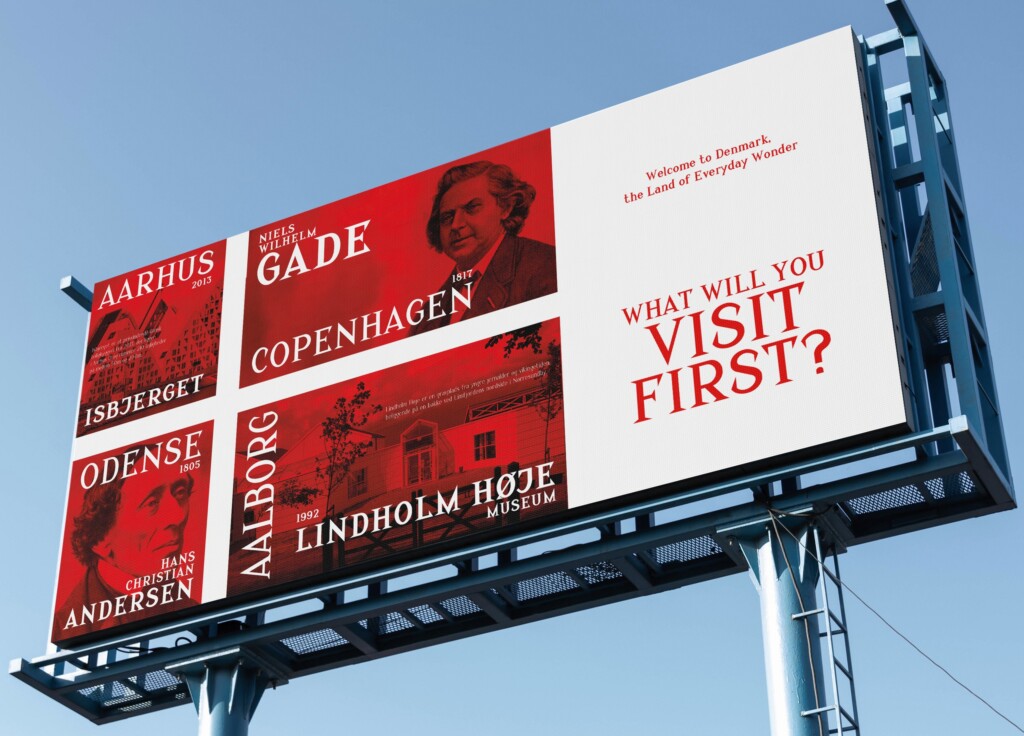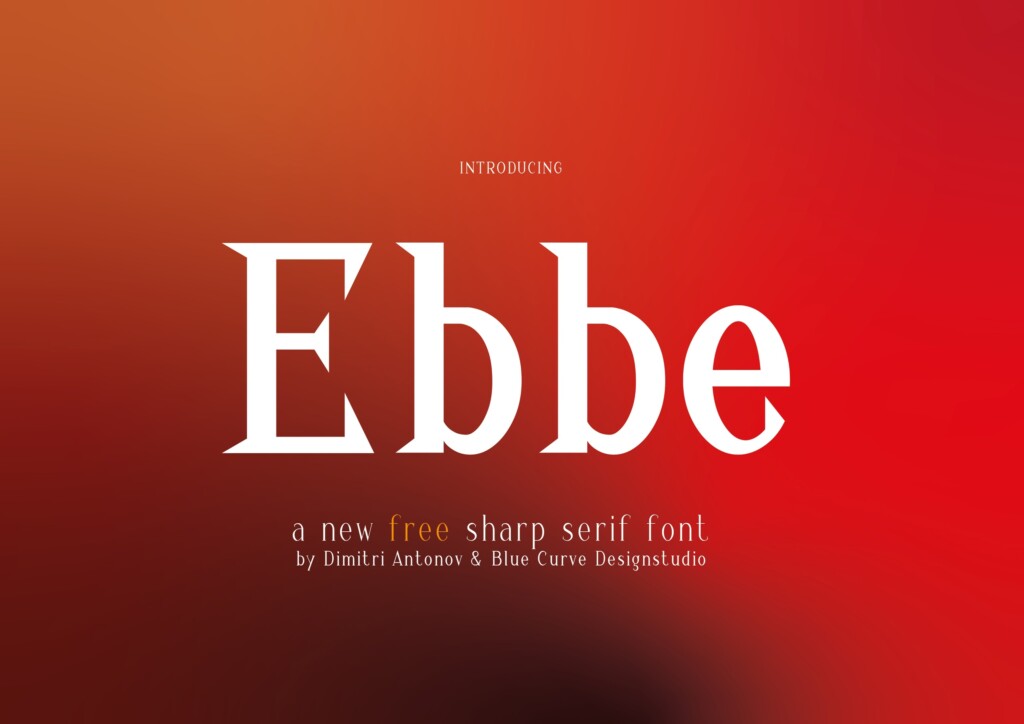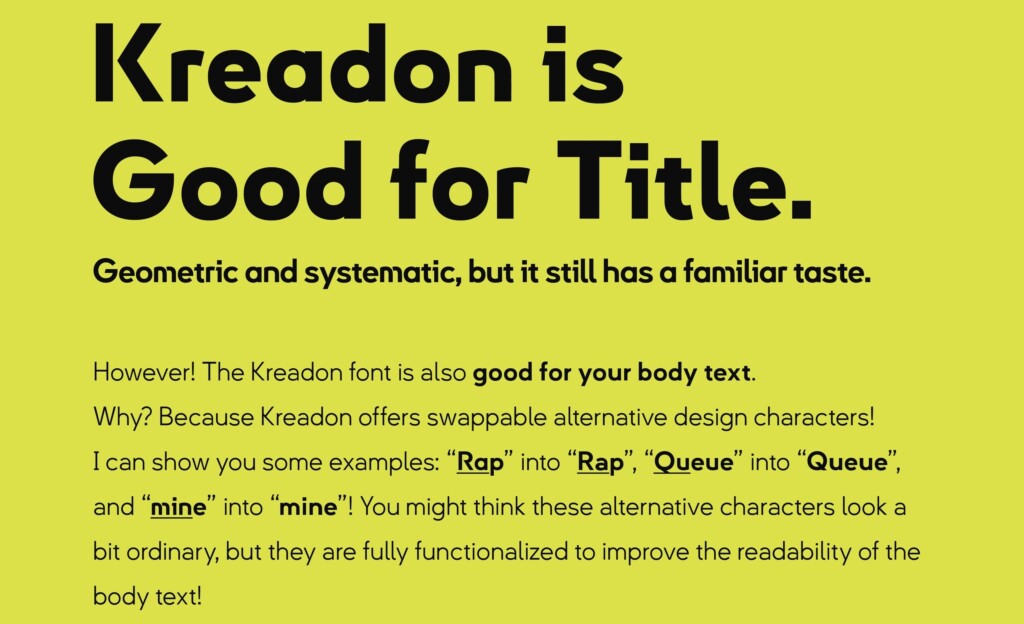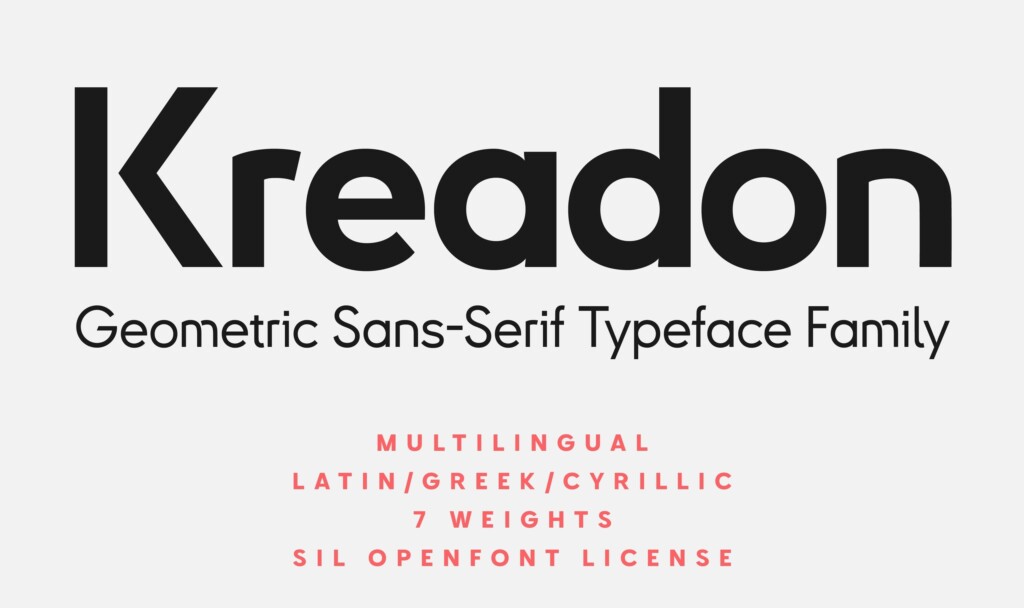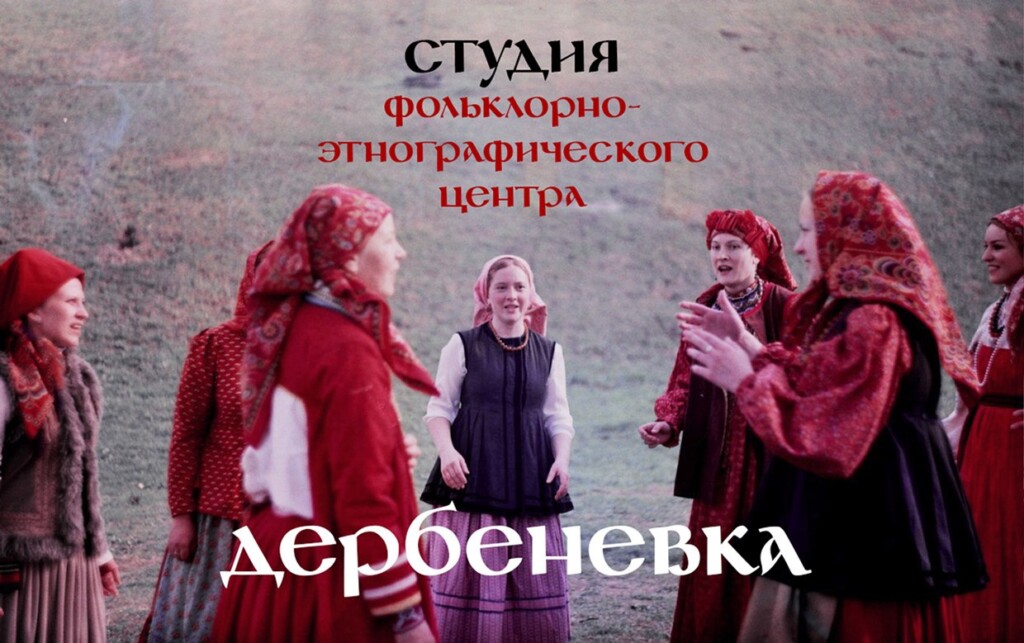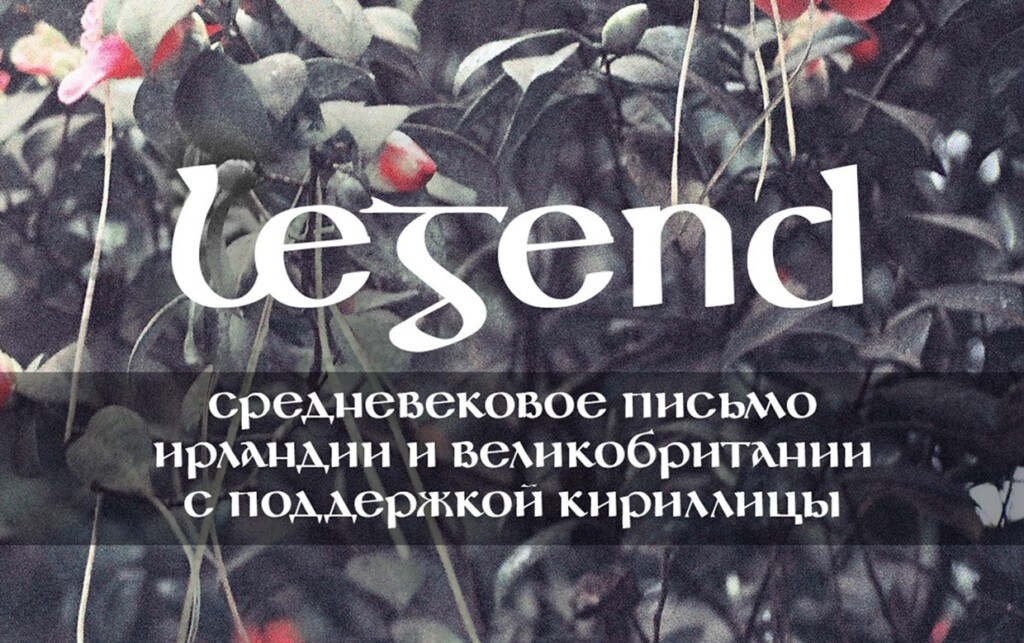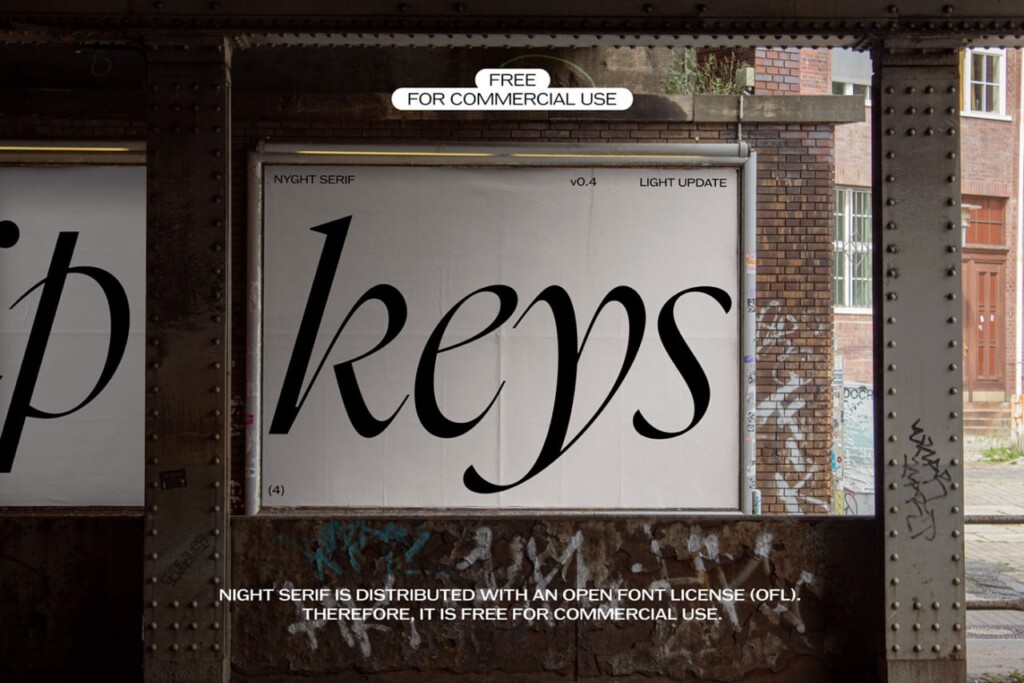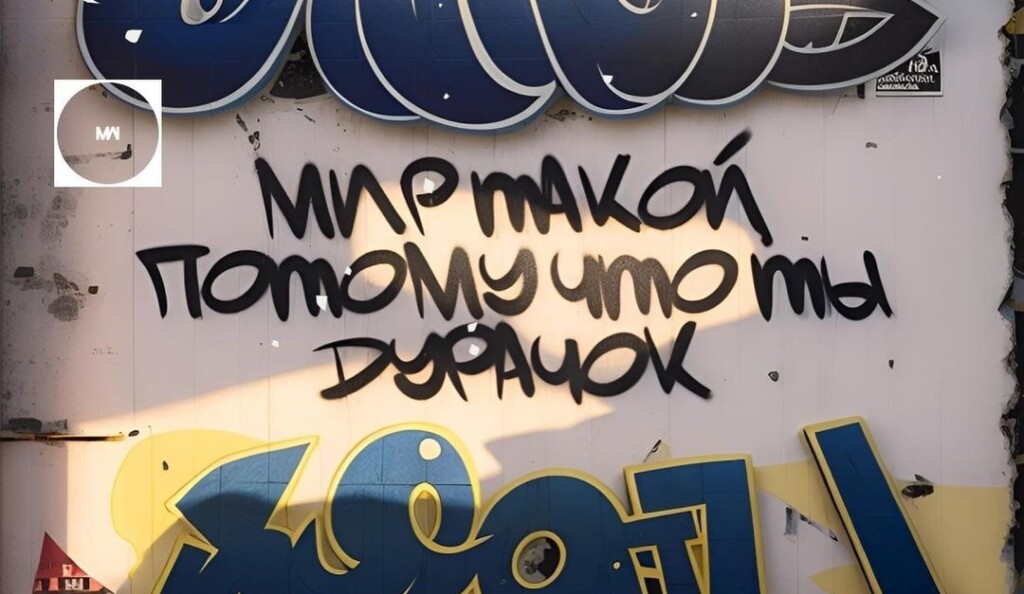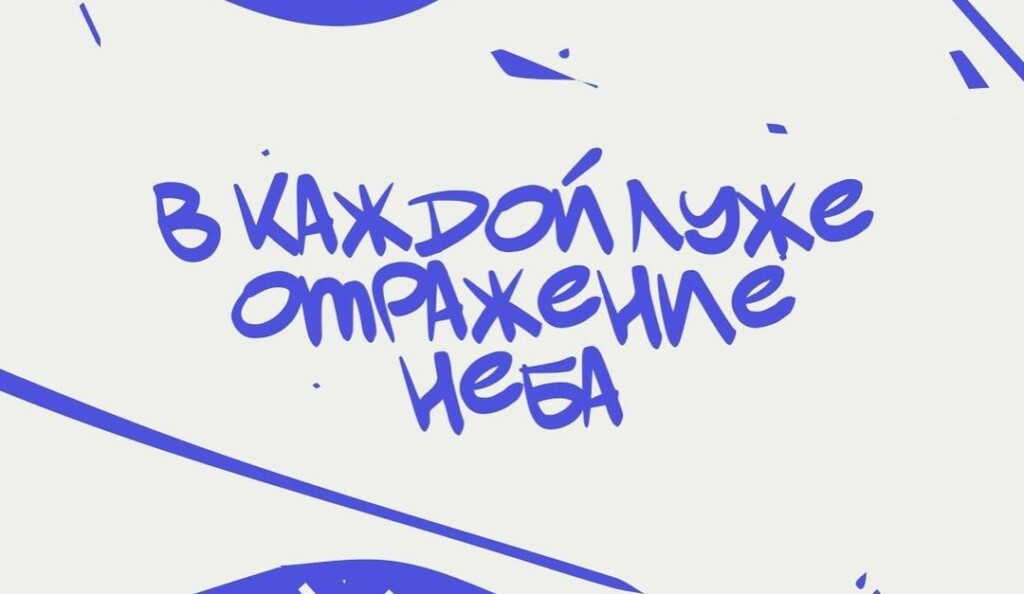
Бесплатные шрифты для дизайнеров
Выбор шрифта — не просто эстетическая, это важная и функциональная задача. В зависимости от целей, дизайнерский шрифт может служить для расстановки акцентов и выделения ключевых моментов, передачи информации и формализации текста. К тому же, он несёт за собой определённую семантическую нагрузку: от того, какой шрифт выберет дизайнер, зависит, как будет воспринят проект в целом.
Акцидентные шрифты
Для начала давай разберёмся в терминологии. Дизайнерские шрифты в основном используются для двух целей — выделить важную информацию (например, заголовок, ключевую фразу, основной вывод и т.д.) или оформить основной текст на слайде, странице и любой другой дизайн-области. Отсюда выделяют два вида шрифтов: акцидентные и наборные.
Акцидентные шрифты — это шрифты, которые используются для расстановки акцентов и выделения отдельных текстовых блоков. Они декоративные и зачастую трудночитаемые, поэтому такие шрифты удачно смотрятся в коротких, небольших текстах, а в объёмных же текстовых блоках они снижают уровень восприятия информации и ухудшают опыт взаимодействия с материалом.
Титульный слайд с акцидентным шрифтом
Пример использования акцидентного шрифта в презентации. Источник: Банк слайдов B&S
• Каждый акцидентный шрифт имеет свой характер, который задаёт настрой всему дизайн-проекту: одни шрифты ассоциируются с лёгкостью, дружелюбностью, весельем, другие — с силой, влиянием, серьёзностью, третьи — с элегантностью, премиальностью, дороговизной и т.д.
• При подборе акцидентного шрифта важно учитывать, какие эмоции и настроения он отражает. Несоответствие темы и семантики шрифта станет грубой ошибкой, которая испортит впечатление о проекте.
• Примеры: Neue Metana Next, Kill Me, BASE&BLOOM CYR, Plantype, Cracking Sans, Groovy Knock, Merlo Rakasha, Sea Octopus и другие.
Наборные шрифты
Наборные шрифты — шрифты, которыми набираются тексты, предназначенные для чтения. Они легко воспринимаются, за счёт чего используются для оформления больших информационных блоков. Основная цель наборных шрифтов — создать условия для быстрого чтения и качественного усвоения материала. Поэтому такие шрифты не имеют ярко выраженного характера и часто визуально не примечательны, хоть и отличаются отдельными деталями.
Гротеск на слайде
Пример использования наборного шрифта в презентации. Источник: Банк слайдов B&S
Наборные шрифты делятся на гротески (sans) и антиквы (serif). Гротески — шрифты без засечек. Они простые и очень универсальны: благодаря своему минималистичному и современному виду гротески отлично вписываются в дизайн-проект любой тематики. Гротески подходят как для небольшого, так и для крупного текстового блока.
• Примеры: Futura, Gilroy, Muller, Arial, Helvetica, Montserrat.
Шрифты без засечек на слайде
Источник: Банк слайдов B&S
Антиквы — шрифты с засечками на концах букв, которые уже накладывают определённые ограничения в использовании. Антиквы характерны для серьёзных, классических, солидных проектов. Они будут плохо смотреться в дизайне, ориентированном на молодёжь или на инновационные идеи.
• Примеры: Georgia, Garamond, Rockwell.
Шрифты с засечками на слайде
Источник: Банк слайдов B&S
Итак, в основных видах шрифтов и их назначении мы разобрались: акцидентные шрифты привлекают внимание и задают настроение проекту, а наборные — обеспечивают комфортное восприятие. Однако независимо от того, какой шрифт используется, стоит учитывать авторские права на него. Все шрифты, будь то акцидентные или наборные, могут быть использованы как в личных, так и в коммерческих целях при наличии соответствующей лицензии.
Для коммерческого использования
Чаще всего дизайнеры используют шрифты в коммерческих целях — создают фирменный стиль компании и занимаются брендингом, оформляют бизнес-презентации, веб-сайты и рекламные материалы. В таких проектах шрифт будет приносить коммерческую выгоду (прибыль), поэтому его использование должно быть законно: у выбранного шрифта должна быть соответствующая лицензия.